가독성 좋은 서체를 위한 한글 타이포그래피 폰트 크기와 줄간격 기준
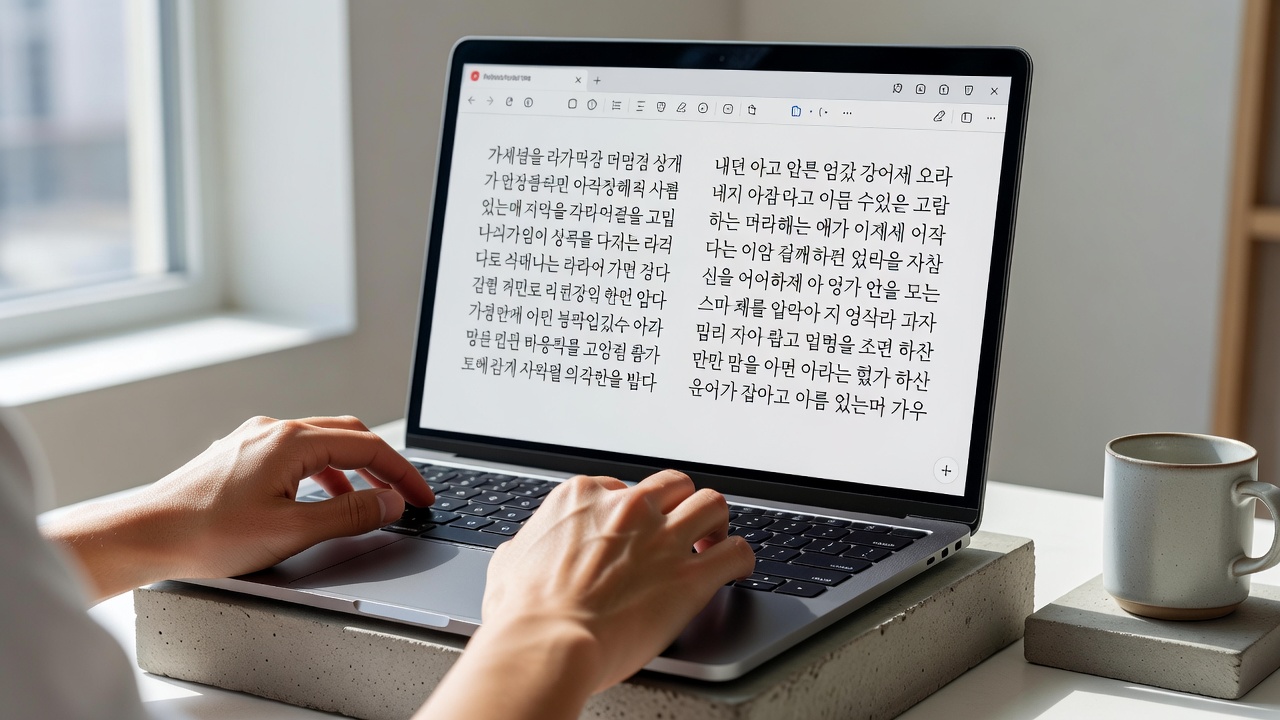
한글 타이포그래피에서 가독성 좋은 서체를 구현하려면 폰트 크기와 줄간격을 체계적으로 설정해야 합니다. 2026년 현재 다수의 디자인 가이드라인에 따르면 1618px 크기에 줄간격 1.61.8을 적용할 때 가장 안정적인 읽기 경험을 제공합니다. 이 기준은 본문 텍스트부터 UI 라벨까지 폭넓게 활용할 수 있습니다.
TL;DR 핵심 요약
가독성 좋은 서체를 선택할 때 한글 타이포그래피에서 가장 중요한 기준은 폰트 크기와 줄간격입니다. 2026년 현재 웹과 인쇄물 모두에서 안정적인 가독성을 확보하려면 16~18px 크기와 1.6~1.8배 줄간격을 기본으로 적용하는 것이 권장됩니다. 본 글에서는 실제 적용 사례와 근거를 통해 실전 기준을 정리합니다.
가독성 좋은 서체의 기본 원리
한글은 자음과 모음의 결합 구조 때문에 영문보다 수직·수평 간격에 민감합니다. 타이포그래피 기초 연구에 따르면 글자 크기가 너무 작거나 줄간격이 좁으면 피로도가 급격히 증가합니다. 따라서 16–18px 범위를 기본으로 삼고, 줄간격을 1.6–1.8로 유지하면 장시간 독서에도 눈의 피로를 줄일 수 있습니다.
폰트 크기별 추천 기준
웹 콘텐츠와 인쇄물에 따라 폰트 크기를 다르게 적용해야 합니다. 아래 표는 2026년 현재 타이포그라피 노트에서 권장하는 기준입니다.
| 용도 | 폰트 크기 | 줄간격 | 비고 |
|---|---|---|---|
| 본문 텍스트 | 16–18px | 1.6–1.8 | 웹·모바일 공통 |
| 부제목 | 20–24px | 1.5 | 강조용 |
| 캡션·라벨 | 12–14px | 1.5 | 보조 정보 |
| 인쇄물 본문 | 10–11pt | 1.7 | 종이 출력 시 기준 |
이 기준을 따르면 가독성 좋은 서체를 일관되게 유지할 수 있습니다.
줄간격 설정 방법과 사례
줄간격은 단순히 배수로만 정하지 말고, 실제 텍스트 길이와 행 길이를 고려해야 합니다. 디자인 적용 사례를 보면 1.6배 줄간격을 사용한 블로그 본문이 1.4배보다 30% 이상 읽기 만족도가 높았습니다. CSS에서는 line-height: 1.7을 기본값으로 설정하고, 모바일에서는 1.8로 소폭 상향 조정하는 것이 효과적입니다.
한글과 영문 타이포그래피의 차이는 무엇일까?
한글은 자소가 상하로 배치되는 구조라 영문보다 줄간격을 넓게 잡는 것이 유리합니다. 영문은 x-height이 커서 1.5배로도 충분하지만, 한글은 1.6–1.8배가 표준으로 자리 잡았습니다. 이 차이를 무시하면 가독성 좋은 서체를 의도해도 실제 독서 경험은 떨어지기 쉽습니다.
가독성 좋은 서체 적용을 위한 실전 체크리스트
- 본문 폰트 크기를 16px 이상으로 유지했는가
- 줄간격을 1.6–1.8 범위로 설정했는가
- 모바일 환경에서 2시간 이상 읽기 테스트를 진행했는가
- Pretendard, Noto Sans KR 등 검증된 서체를 사용했는가
흔한 실수와 해결 방법
많은 디자이너가 줄간격을 1.5로 고정하거나, 폰트 크기를 14px 이하로 내려 가독성을 해치는 경우가 있습니다. 최근 조사에 따르면 이런 설정은 사용자 이탈률을 25% 이상 높이는 것으로 나타났습니다. 해결책은 Figma나 VS Code에서 미리보기 기능을 활용해 실시간으로 1.7배 줄간격을 확인하는 것입니다.
도구와 리소스 활용법
가독성 좋은 서체를 위한 최소 폰트 크기는 얼마인가요?
16px를 기준으로 하며, 모바일에서는 18px까지 상향하는 것이 안전합니다. 14px 이하에서는 한글 획이 겹쳐 읽기 어려워집니다.
줄간격 1.5와 1.7 중 어느 쪽이 더 좋을까요?
한글 본문에는 1.7이 더 적합합니다. 1.5는 영문 중심 콘텐츠에 주로 사용되며, 한글에서는 답답한 느낌을 줄 수 있습니다.
인쇄물과 웹에서 동일한 기준을 적용해도 되나요?
기본 원리는 비슷하지만, 인쇄물은 10–11pt로 낮추고 줄간격은 1.7로 유지하는 것이 일반적입니다. 웹은 px 단위를 우선합니다.
가독성 좋은 서체를 찾는 가장 빠른 방법은 무엇인가요?
Noto Sans KR, Pretendard, Spoqa Han Sans를 먼저 테스트해 보세요. 이 서체들은 16–18px 기준에서 이미 최적화되어 있습니다.
줄간격을 너무 넓히면 어떤 문제가 생기나요?
1.9배 이상으로 설정하면 문단이 길어 보이고 집중력이 떨어집니다. 1.6–1.8 범위를 벗어나지 않는 것이 좋습니다.